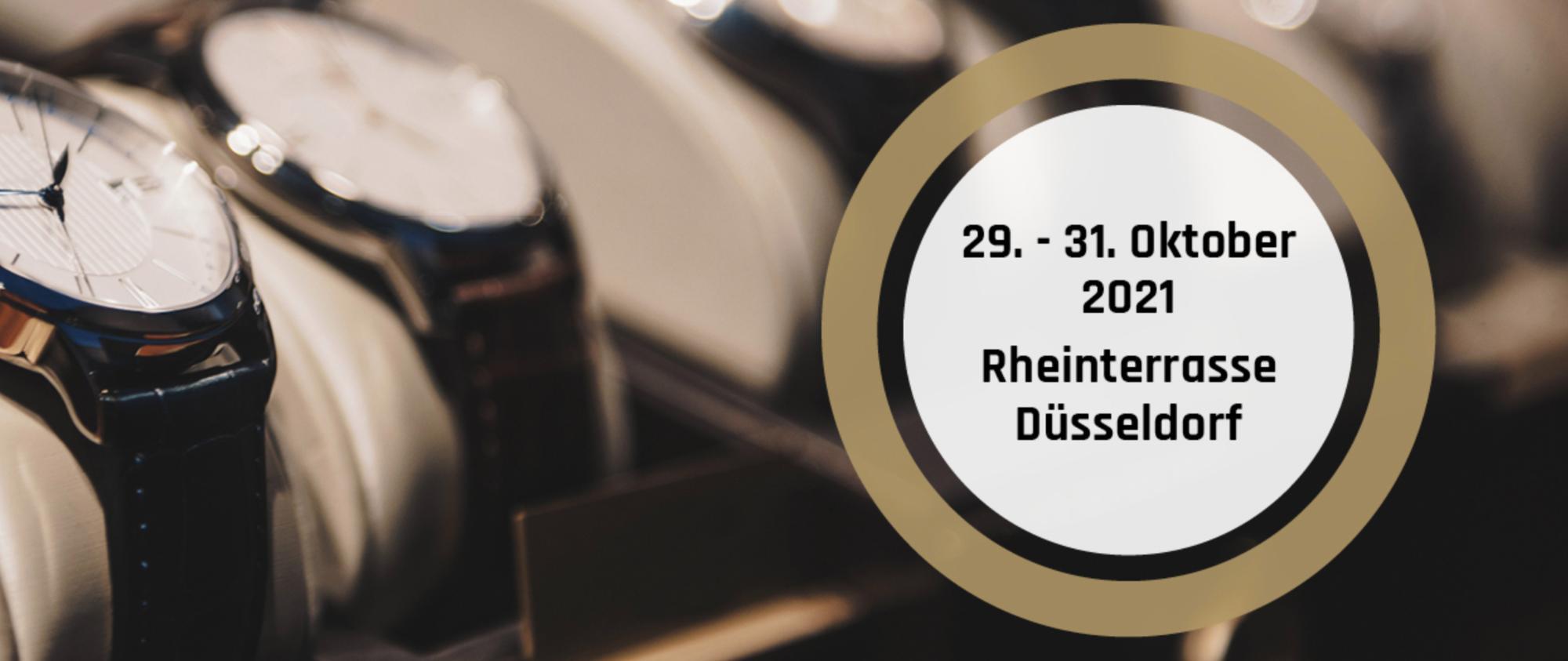
Geometrische Grotesk mit auffälliger s-Form (aktuelle Werbung WATCHTIME Düsseldorf)
mal abgesehen vom falschen "bis"-Strich in der Anwendung, kennt jemand diesen Font?
Anzeige in der aktuellen PAGE: Uhrenausstellung Watchtime Düsseldorf